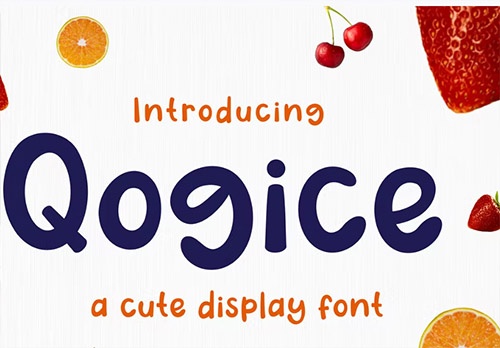
فونت رایگان انگلیسی Qogice
فونت انگلیسی Qogice
دانلود رایگان فونت انگلیسی مدرن Qogice
فونت Qogice یک فونت مدرن و نمایشگر برجسته و معتبر است. این فونت برای هر پروژه برندسازی مانند لوگو، چاپ تی شرت، esport و بسیاری موارد دیگر مناسب است. برجسته در طیف گسترده ای از زمینه ها. برای دریافت فونت رایگان انگلیسی Qogice از جی اف ایکس دانلود به ادامه مطلب مراجعه کنید.
دانلود رایگان فونت مدرن Qogice